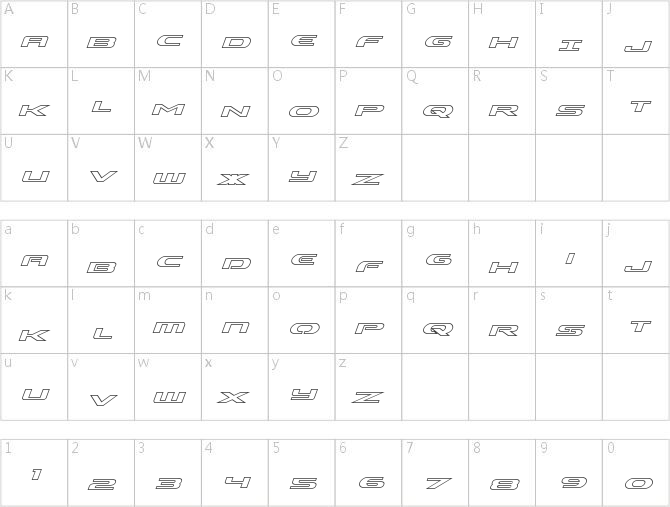
Alpha Men Outline Italic 詳情頁
Alpha Men Outline Italic字體字庫是一款讓人賞心悅目、百看不厭的英文字體,適合各類廣告和產(chǎn)品包裝設(shè)計(jì)應(yīng)用,字體大小0.04MB,格式為ttf字體,上傳用戶是多喝燙水,作者/版權(quán)方為未知